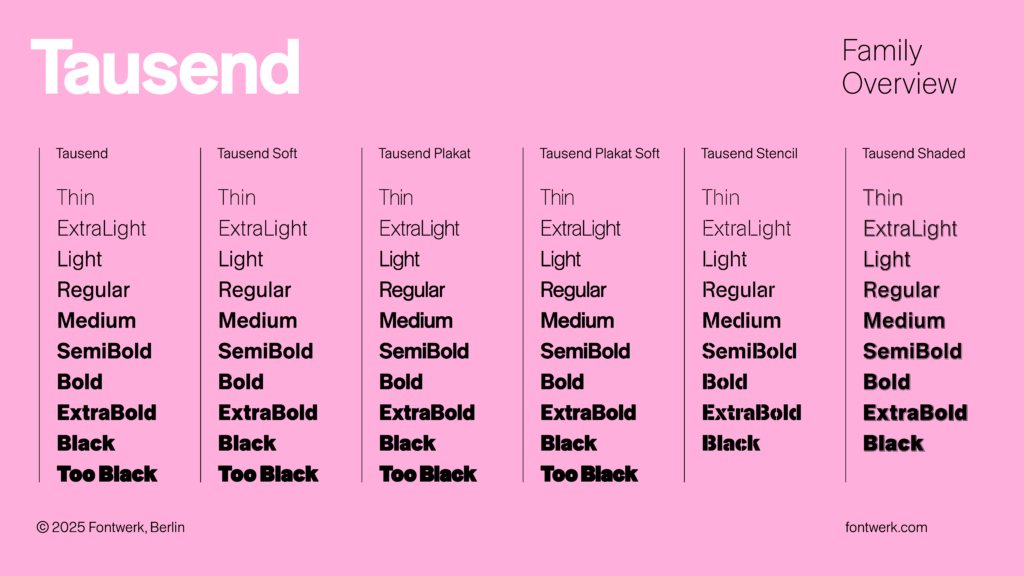
Nos ha llegado a la redacción una tipografía que, la verdad, nos ha atrapado desde el primer vistazo. Se llama Tausend y es el último lanzamiento de la fundición berlinesa Fontwerk. Una grotesca que respira tradición, pero que está pensada con la mirada puesta en los nuevos tiempos.
No es tan habitual que una grotesca —ese género tipográfico tan explorado, tan revisado, a veces incluso saturado— consiga llamar la atención a estas alturas. Pero Tausend lo hace. Y no solo por su estética, sino por lo que representa: un homenaje al linaje histórico de las grotescas alemanas, como Akzidenz-Grotesk, pero reinterpretado desde la tecnología actual y, sobre todo, desde la mirada inquieta y precisa de sus autores: Christoph Koeberlin y Gabriel Richter.
Fontwerk, la fundición que la publica, tal vez no sea aún un nombre tan conocido fuera del circuito más especializado. Con sede en Berlín, se ha ganado en los últimos años una reputación impecable gracias a un catálogo que combina calidad técnica y personalidad. Su filosofía es clara: crear tipografías que no sean solo funcionales, sino también capaces de contar algo. Y Tausend es, posiblemente, su propuesta más ambiciosa hasta la fecha.
Todo empezó con una ‘a’
La historia de esta tipografía tiene algo de poético. Todo empezó hace tres años con un simple ‘a’. Mientras diseñaba Tresor, Christoph Koeberlin trazó una versión de la letra ‘a’ que se alejaba del camino que ese proyecto pedía. Había algo en ese carácter —una ligereza en la curva, una apertura sugerente, una inclinación casi juguetona— que le hizo pensar que ahí había otra historia por contar. Y no se equivocaba.
Koeberlin decidió entonces asociarse con Gabriel Richter, diseñador alemán afincado en Japón, conocido por su trabajo en tipografías como FF Infra, Massimo Grafia o Neue Television, y por su forma de abordar las grotescas desde ángulos poco convencionales. Juntos, comenzaron a desarrollar ese ‘a’ en lo que terminaría siendo Tausend, un proyecto que ha ido creciendo hasta convertirse en un verdadero sistema tipográfico.
No es un revival, es una declaración
Tausend bebe directamente de la tradición tipográfica alemana, pero no es un revival al uso. No busca reproducir el pasado, sino reinterpretarlo. Su estructura respeta las reglas de la grotesca: bajo contraste, terminales rectas, formas robustas. Pero introduce pequeñas desviaciones que la hacen especial. Las curvas tienen un ligero sobrepeso en la parte superior, las aperturas son más generosas en ciertos caracteres, y algunos detalles parecen diseñados para romper, con elegancia, la rigidez del género.
El resultado es una tipografía que se siente familiar, pero al mismo tiempo fresca y rotunda. Como ellos mismos la definen: “brutalmente honesta, orgullosa y segura”. Una fuente pensada para marcas que buscan transmitir confianza, pero también una cierta actitud.
Mil posibilidades
Y si su apariencia seduce, su estructura técnica no se queda atrás. Tausend no es solo una familia tipográfica: es prácticamente un universo. Gracias a la tecnología variable, ofrece más de mil pesos —sí, mil—, desde los más ligeros hasta un extremo “Too Black” que roza lo expresionista. Además, está organizada en seis subfamilias: Tausend, Tausend Plakat, Tausend Soft, Tausend Plakat Soft, Tausend Stencil y Tausend Shaded. Cada una con matices específicos pensados para distintos usos, desde cuerpos de texto hasta titulares o diseño editorial y digital.
Uno de los grandes aciertos es la incorporación de tamaños ópticos. Esto significa que la tipografía adapta sus proporciones, aperturas y detalles según el cuerpo en que se use. Algo que, en términos prácticos, mejora la legibilidad y evita esos ajustes manuales que cualquier diseñador conoce bien: tracking, escalados o cambios en la mancha tipográfica según el soporte.
Los nombres detrás de la fuente
Parte de lo que hace que Tausend funcione tan bien es la trayectoria y la complicidad de sus dos diseñadores.
Christoph Koeberlin no necesita muchas presentaciones en el mundo tipográfico. A lo largo de su carrera ha trabajado para algunas de las fundiciones y marcas más reconocidas del mundo: FontFont, Grilli Type, Swiss Typefaces, TypeMates o Miles Newlyn, además de empresas como TikTok, Ebay, Volkswagen, Lufthansa, Porsche, Deutsche Bank, Figma o el Gobierno alemán. Es, sin duda, uno de los ingenieros tipográficos más valorados de Europa.
Pero más allá de su faceta técnica, Koeberlin es también un diseñador con olfato. Suyo es, junto a Hannes von Döhren, FF Mark, uno de los grandes éxitos tipográficos de la última década. También es autor de Fabrikat y Pangea, ambas convertidas en bestsellers. Como dato curioso, parte de los beneficios de Pangea los dona de forma permanente a proyectos de conservación del Amazonas. Un perfil técnico, sí, pero con una dimensión creativa y personal muy poco común en este ámbito.
Gabriel Richter, por su parte, es un diseñador con un enfoque más gráfico, más experimental. Su carrera se mueve entre el diseño tipográfico y el diseño visual, lo que explica la energía y el carácter que transmiten muchas de sus fuentes. Ha trabajado para agencias como Büro Uebele y fue responsable, por ejemplo, del desarrollo de Rocky Beach Grotesque, la tipografía oficial de la mítica serie radiofónica alemana Die Drei ???. Actualmente reside en Fukuoka, Japón, desde donde sigue desarrollando proyectos tanto comerciales como personales bajo su sello Nice to Type.
Tausend es, en definitiva, una tipografía que funciona como metáfora de este momento en el que estamos: un presente en el que el diseño necesita ser sólido, flexible y expresivo al mismo tiempo. Un equilibrio delicado entre la tradición y la ruptura, entre la funcionalidad y la personalidad.
Desde la redacción de Gràffica podemos decir que pocas veces una grotesca nos ha parecido tan pertinente, tan bien construida y, a la vez, tan capaz de emocionar.
Y sí, todo empezó con una ‘a’. Pero lo que ha terminado es una fuente que da, literalmente, para mil.